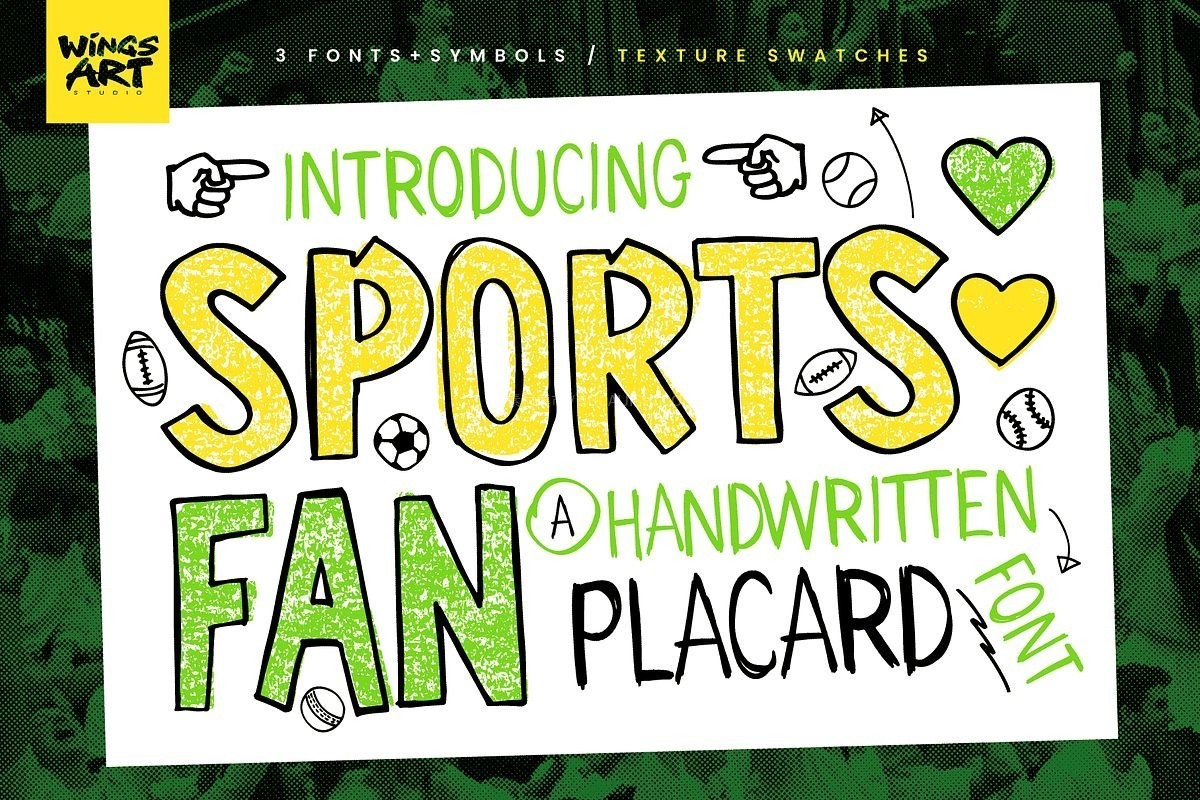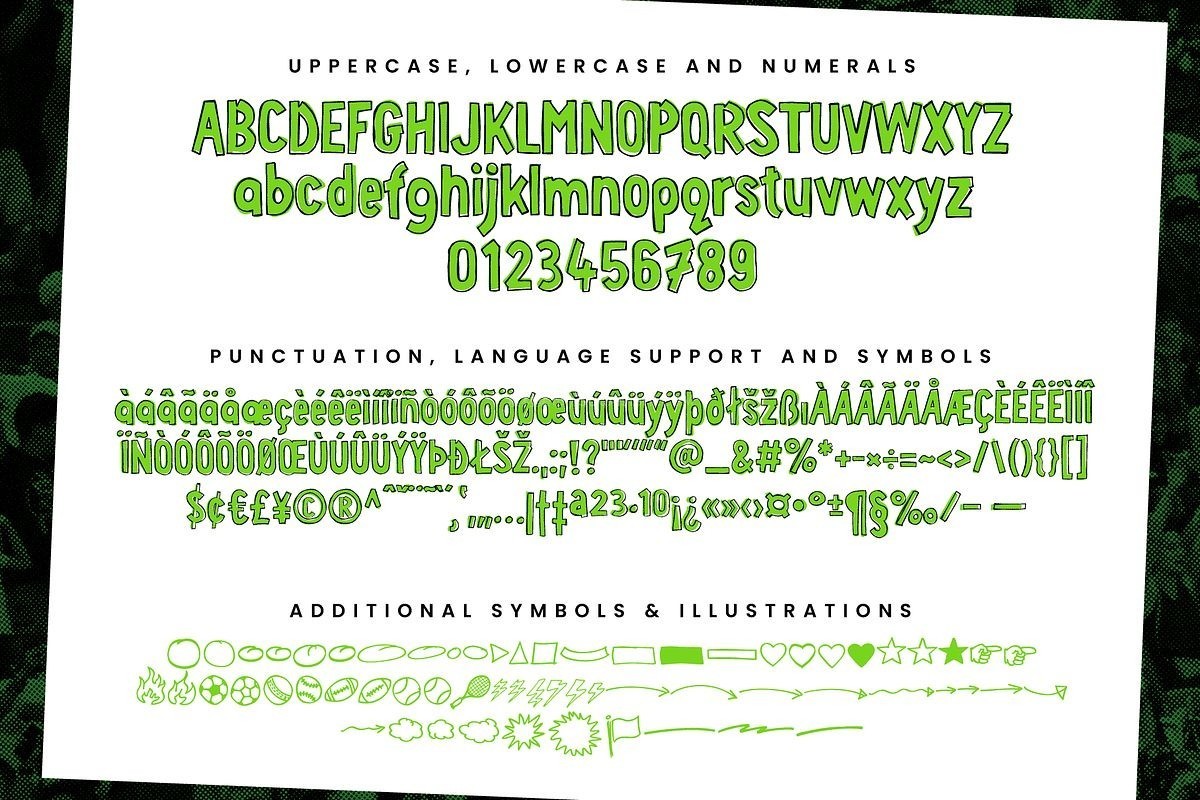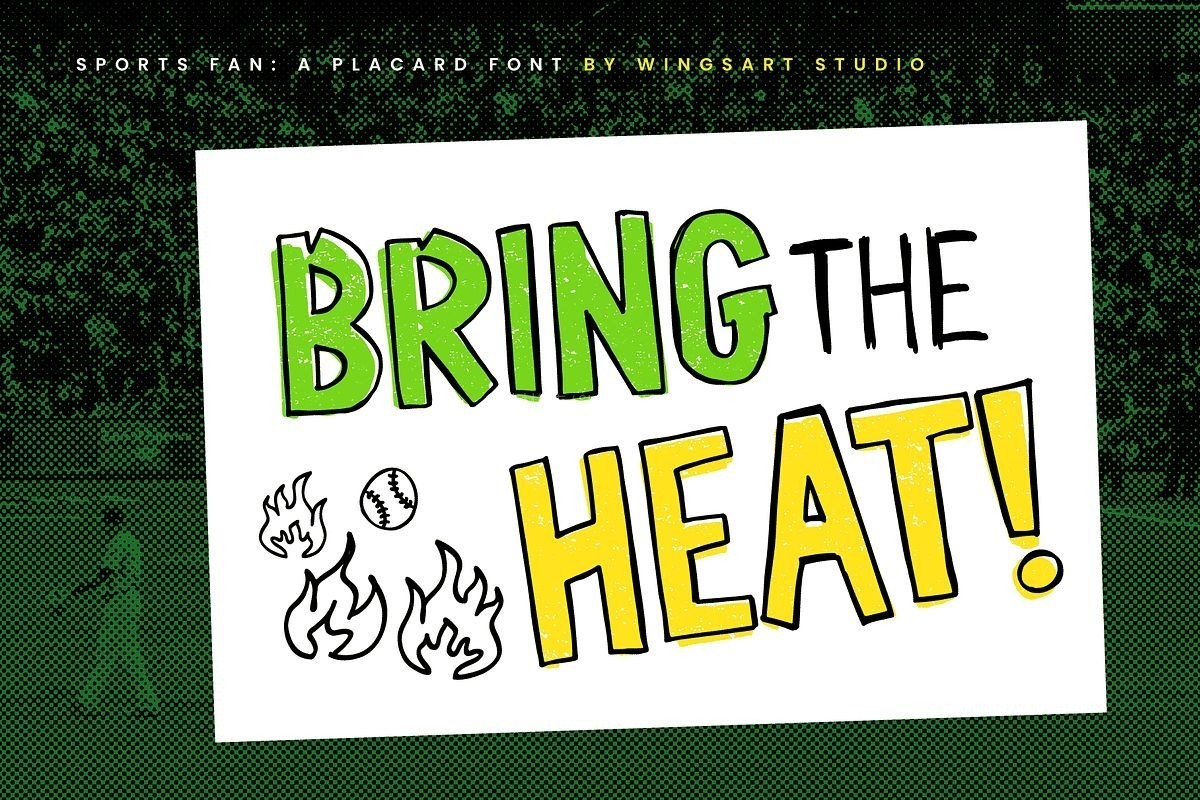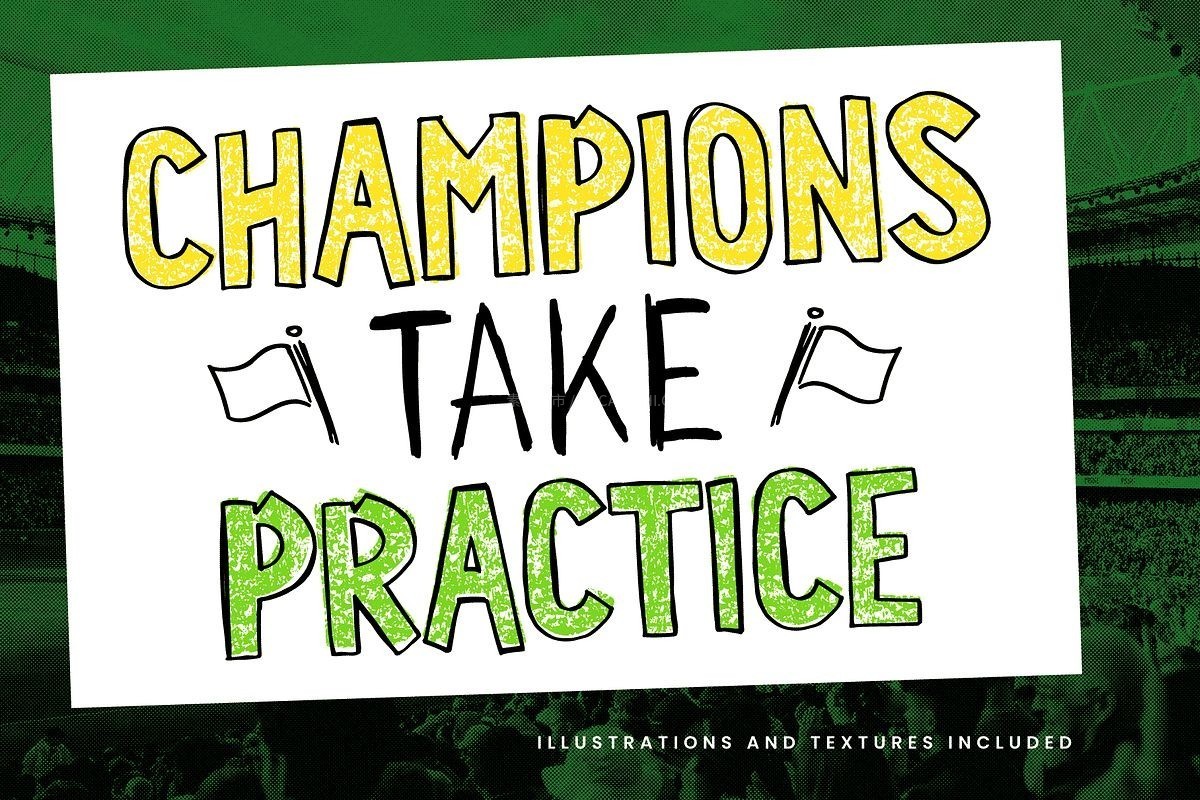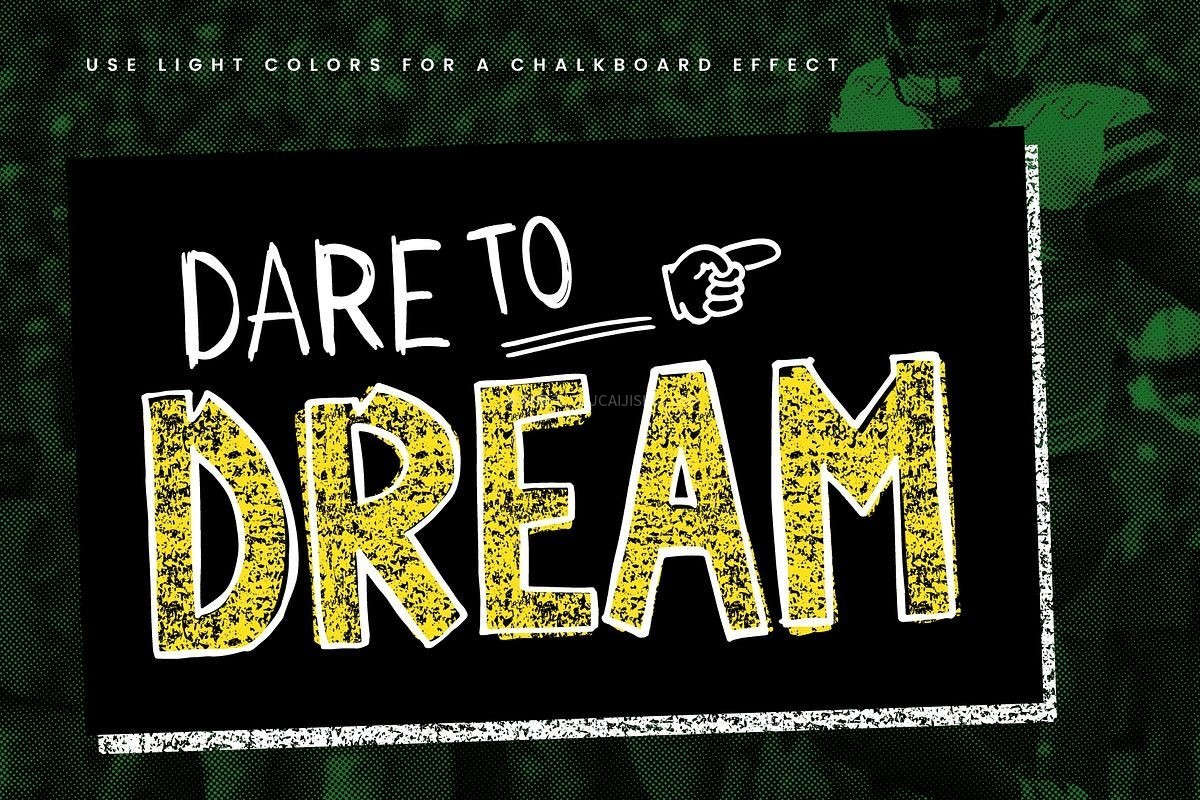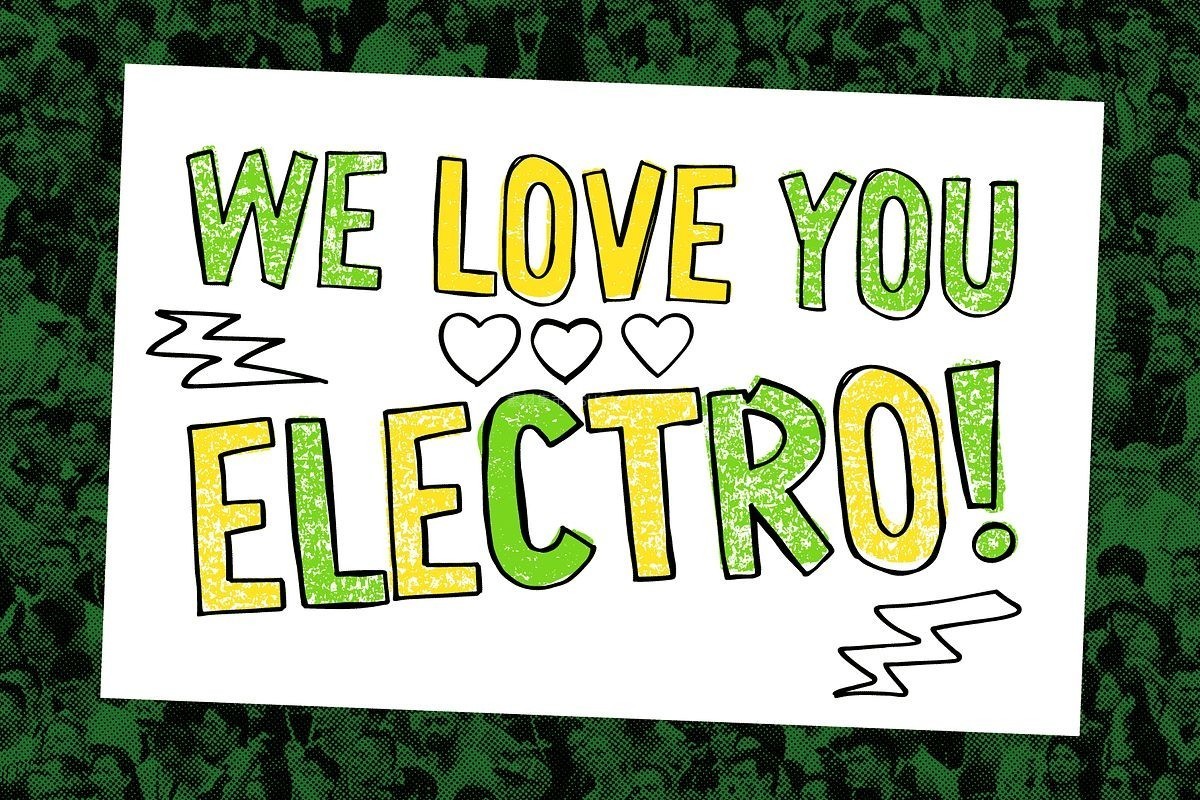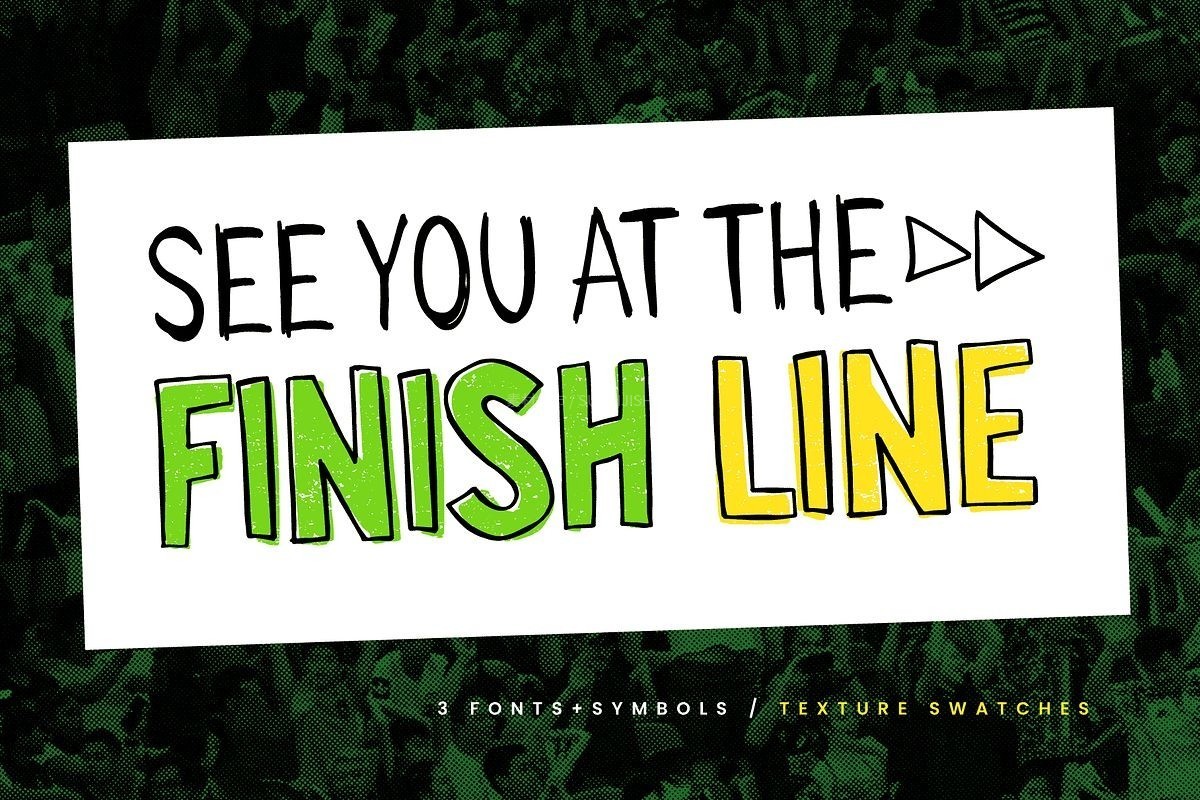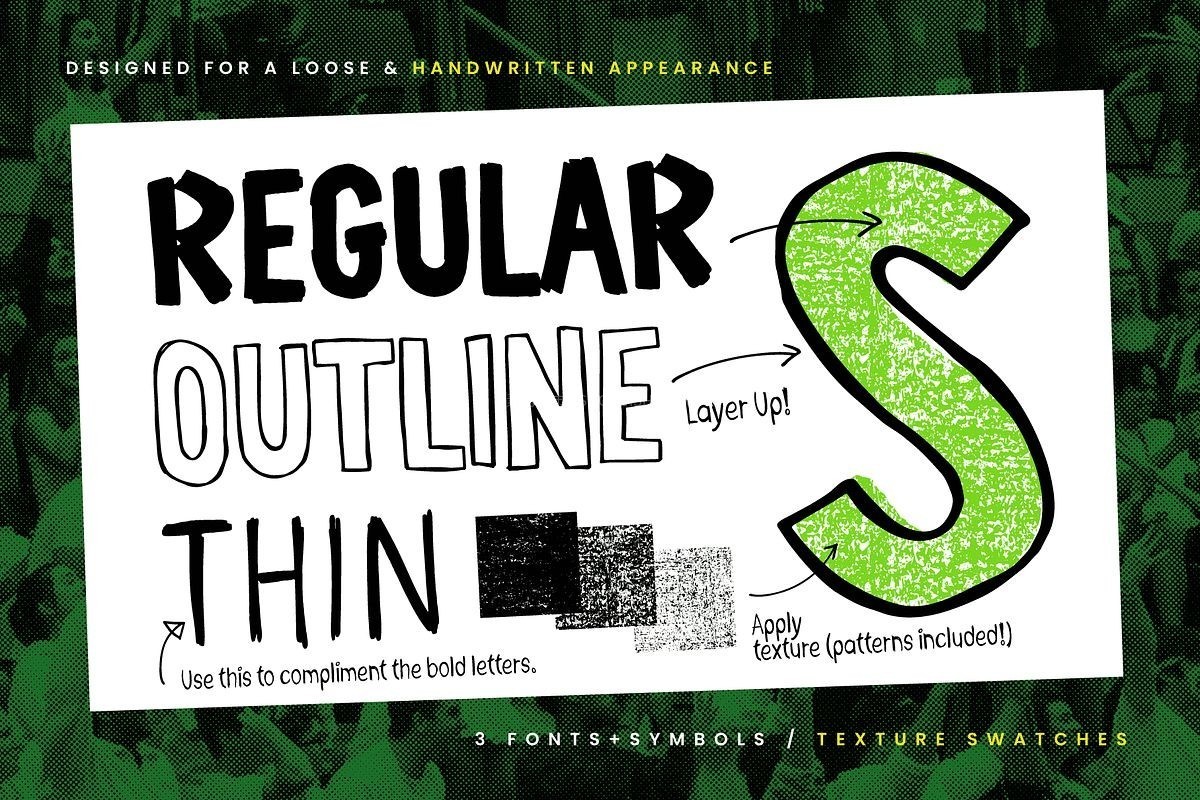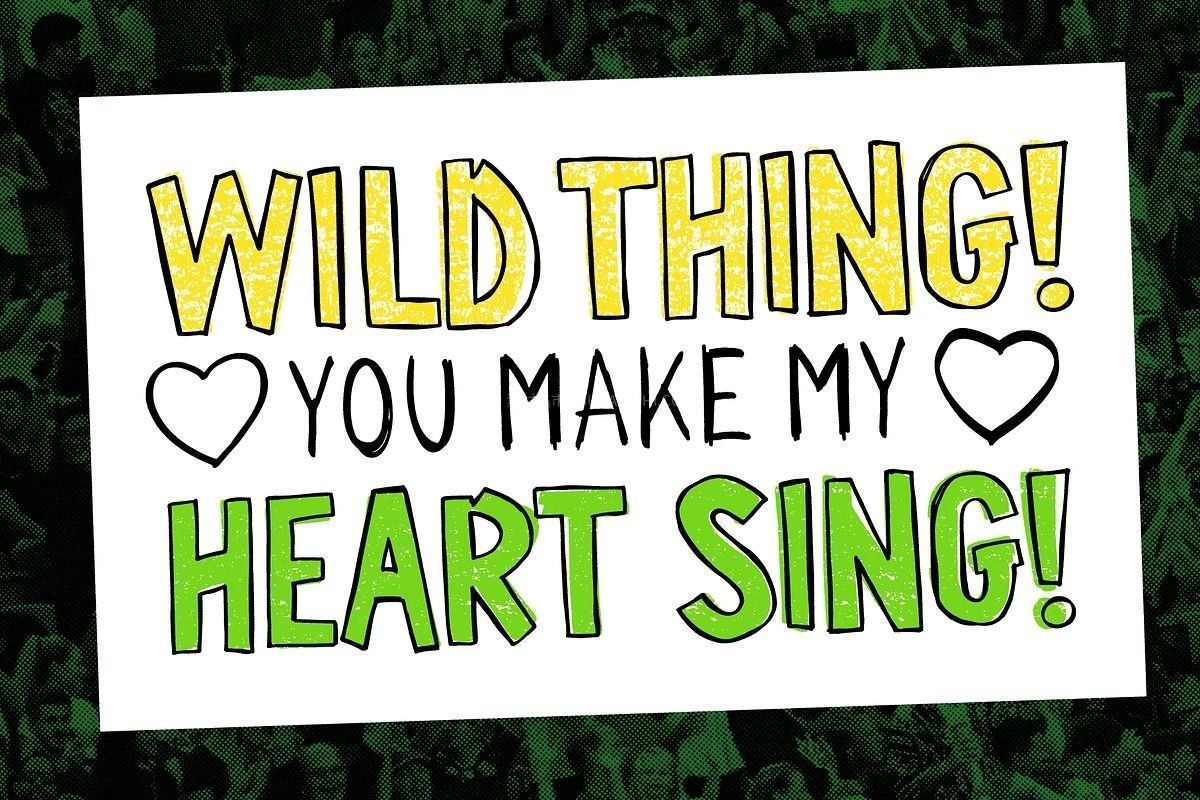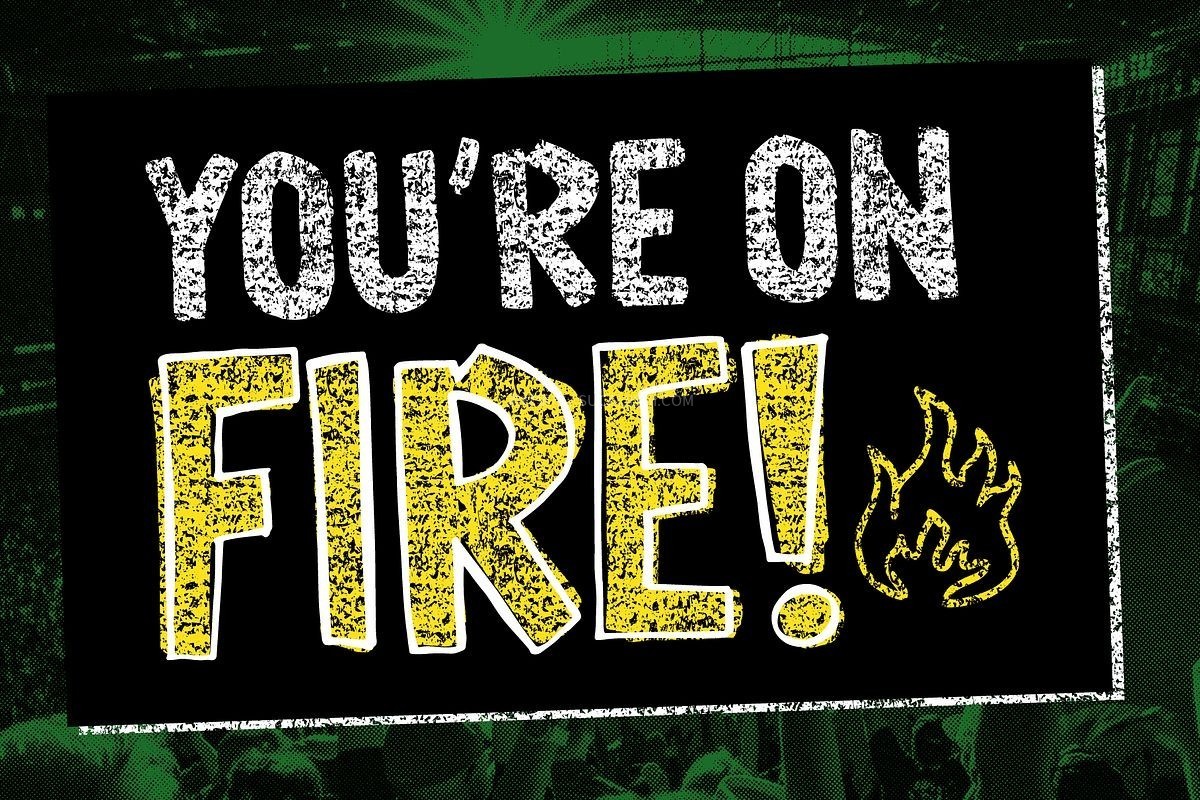
Sports Fan 手写标语英文字体
Sports Fan 是一款充满活力、模仿体育场球迷手写标语牌风格的手写标语字体。提供 Regular、Outline、Thin 三种样式,独特的蜡笔/粉笔质感和童趣的手绘外观脱颖而出。无论是为体育赛事品牌、球迷文化宣传,还是需要打造具有 DIY 感和黑板效果的平面设计,Sports Fan 都能为您的项目注入热情与活力!